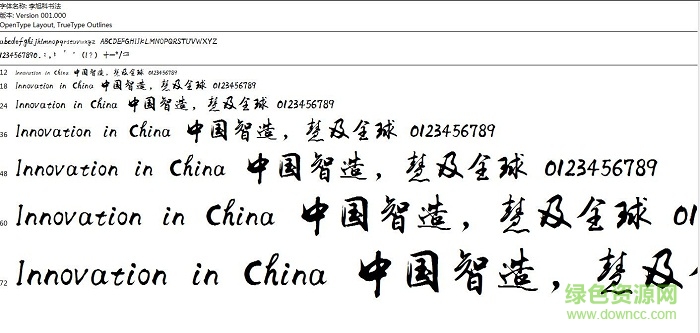
li xuke gbpc euc h字體又叫李旭科書法字體,筆鋒凌厲,運(yùn)筆流暢,蘊(yùn)含骨力,整體結(jié)構(gòu)沒有過多的修飾,線條隨性不刻,用在海報(bào)上表現(xiàn)非常棒,li xuke comic font字體本站也有提供,歡迎免費(fèi)下載!
書法是中國具有三千多年歷史的漢字表現(xiàn)藝術(shù)的主要形式,既有藝術(shù)性,又有實(shí)用性。中國一些企業(yè)主用政壇要人、社會(huì)名流及書法家的題字,作為企業(yè)名稱或品牌標(biāo)準(zhǔn)的字體,比如:中國國際航空公司、健力寶等。
行書是在隸書的基礎(chǔ)上發(fā)展起源的,介于楷書、草書之間的一種字體,是為了彌補(bǔ)楷書的書寫速度太慢和草書的難于辨認(rèn)而產(chǎn)生的?!靶小笔恰靶凶摺钡囊馑?,因此它不像草書那樣潦草,也不像楷書那樣端正。實(shí)質(zhì)上它是楷書的草化或草書的楷化。楷法多于草法的叫“行楷”,草法多于楷法的叫“行草”。